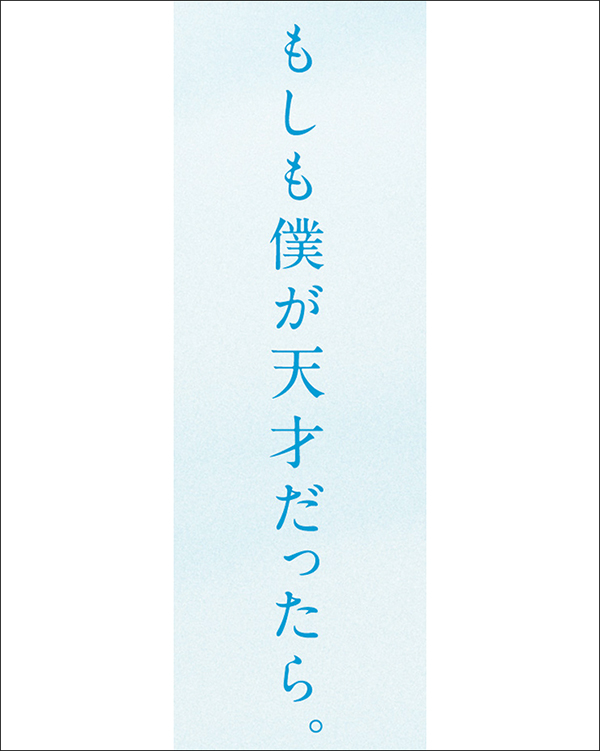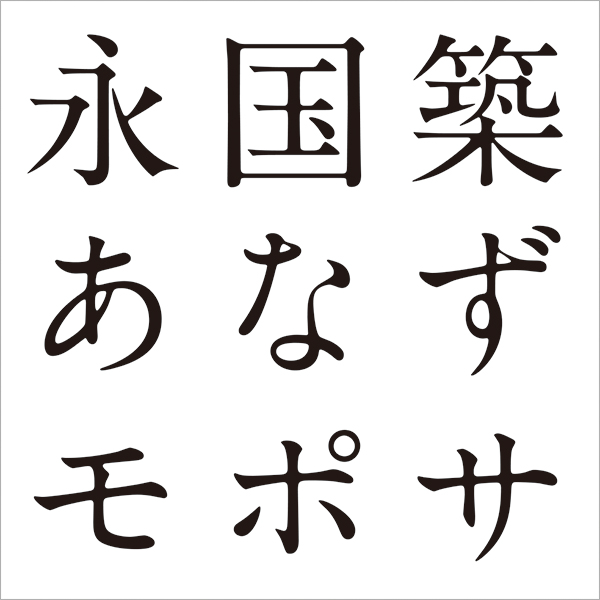
今回は映画『青の帰り道』のポスターの使用フォントをご紹介。本記事はデザイン構成において重要な「フォント」の選定プロセスや加工方法を、貴重なプロの実例から紐解いてデザイン制作に役立てる連載です。
文字のアンバランスさで若者たちの青春模様を
歌手を夢見て上京したカナ、実家を出て一人暮らしを始めたキリ、漠然とデカイことをやると粋がるリョウ、受験に失敗して地元で浪人暮らしのタツオ、できちゃった婚をしたコウタとマリコ、大学に進学したユウキら、高校を卒業した7人の若者たちの人生模様を描いた青春群像劇のポスター。大人への階段を上り始めた彼らの未熟さや希望、成熟していく途中で知る現実や挫折などが、みずみずしいメインビジュアルやアンバランスさを感じさせるタイトルロゴなどで見事にビジュアル化されている。
Font.01「はんなり明朝」「JTCウインM1」
成熟途上の若者の内面を加工した文字で表現
メインタイトルのロゴは、複数の書体を組み合わせたうえで加工したもの。漢字とひらがなの「の」は「はんなり明朝」(Typing Art)、ひらがなの「り」は「JTCウインM1」(エヌアイシィ)がベースに。文字を大きく加工してアンバランスさを持たせることで、作中の若者たちの「青春・若さ・未熟」や、成熟していく途中で知る「現実・大人・挫折」などが表現されている。
Font.02「A1明朝」
タイトルロゴに合わせやわらかな印象の書体に
キャッチコピー部分の文字は、優美なフォルムと画線の交差部分にある墨だまりが印象的なオールドスタイルの明朝体「A1明朝」(モリサワ)。メインタイトルの文字の雰囲気に合わせ、やわらかく温かみのある書体が選択されている。
Font.03「A1明朝」
キャッチコピーと同書体で全体に統一感を持たせる
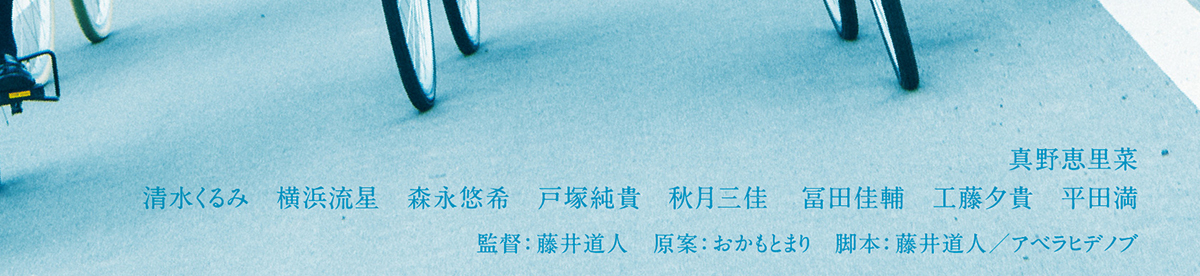
キャストクレジット部分の文字は、キャッチコピーと同じオールドスタイルの明朝体「A1明朝」(モリサワ)。書体を揃えることで統一感を持たせ、作品の世界観をより印象的に伝えるのが狙い。